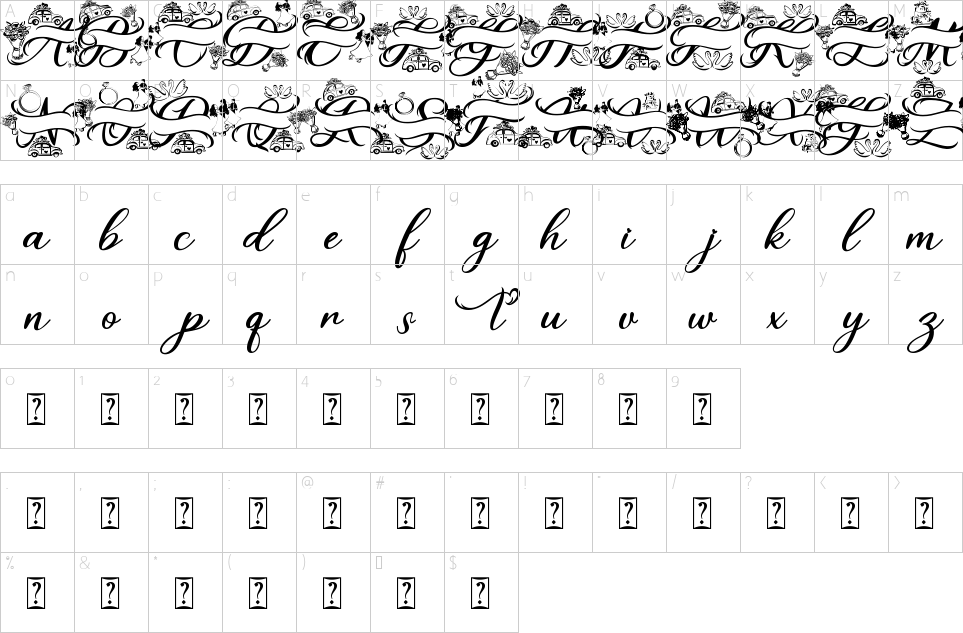
Jasmine Font – Download Grátis
Descubra a Jasmine Font, uma elegante escolha para seus projetos digitais. Desenvolvida por Yoga Letter, essa fonte vem rica em estilo e versatilidade, adequada tanto para criações estéticas quanto para textos informativos. Suas linhas suaves e arredondadas criam um ambiente de tranquilidade e simplicidade que combina perfeitamente com muitos projetos. Com seu design cuidadoso e intuitivo, a Jasmine Font oferece uma experiência visual envolvente, ideal tanto para uso pessoal como profissional, permitindo que você personalize suas criações de acordo com seus objetivos específicos. Sua simplicidade se combina harmoniosamente com o poder da elegância, tornando-a uma opção favorita entre os designers digitais desejosos de adicionar um toque único a seus projetos. Com mais de 194 downloads, Jasmine é mais do que apenas uma escolha; ela é uma parte integrante de muitas criações bonitas e inspiradoras.